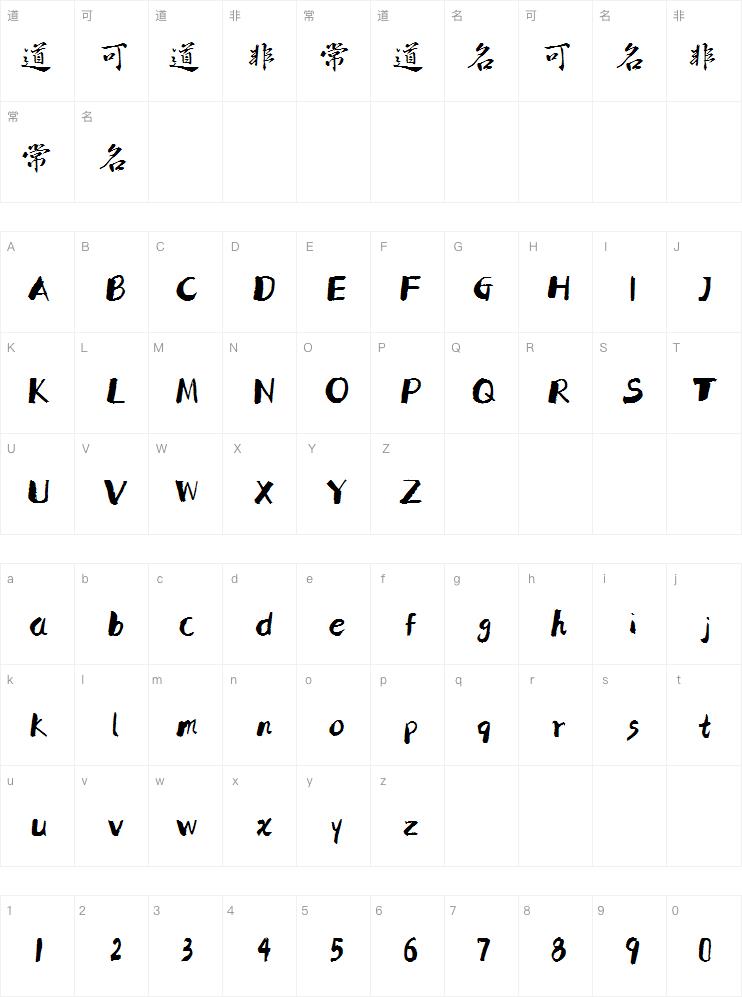
字体的笔画犹如行云流水,一气呵成,每一笔都充满了灵动性和连贯性,给人一种畅快淋漓的书写美感,仿佛书法家在宣纸上肆意挥毫,尽显笔墨韵味。“墨趣古风体” 不仅仅是一种文字表达工具,更是一件艺术品。它将书法艺术与现代设计理念相结合,既保留了传统书法的韵味,又具有现代字体的规范性和实用性,适用于多种设计场景,能够为作品增添独特的艺术氛围。